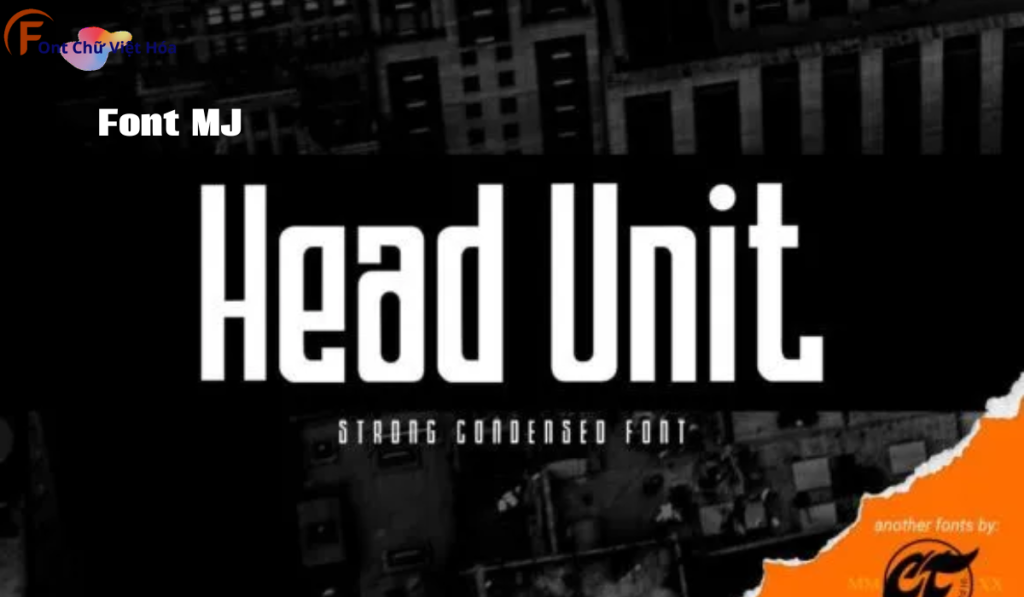
Font MJ HEAD UNIT Việt Hóa
Font MJ HEAD UNIT Việt Hóa là một font chữ không chân mạnh mẽ, thuộc bộ font MJ. Được thiết kế với mục tiêu mang lại sự nổi bật và ấn tượng, font này lý tưởng cho các dự án thiết kế như tiêu đề, quảng cáo, và bao bì sản phẩm. Với các nét chữ đậm và chắc chắn, Font MJ HEAD UNIT Việt Hóa không chỉ dễ đọc mà còn tạo cảm giác mạnh mẽ và quyết đoán. Việc Việt hóa font giúp người dùng dễ dàng sử dụng trong các thiết kế tiếng Việt, mang lại sự tiện lợi và thẩm mỹ cao.